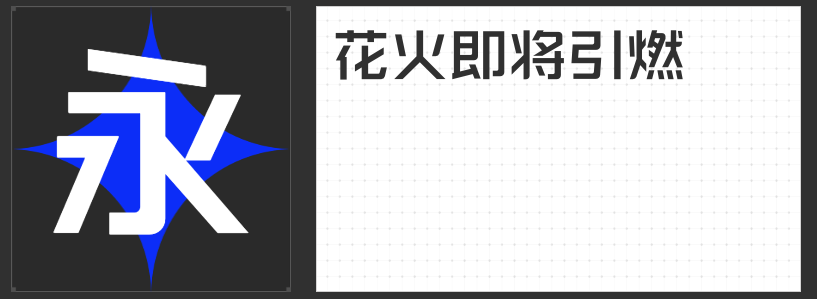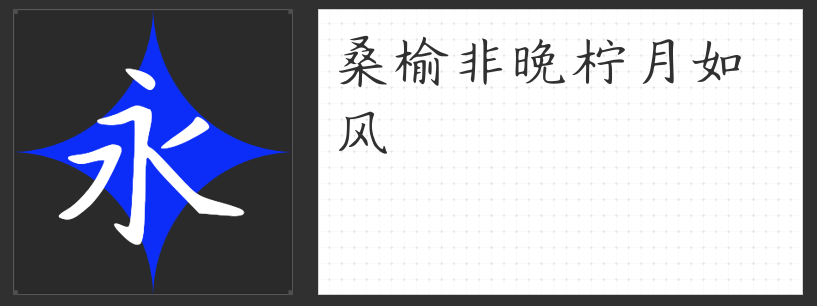
时光回溯:四款怀旧感字体的美学密码
在当代设计追求极简与科技感的浪潮中,怀旧风格以其独特的情感张力与文化厚度,成为连接过去与现在的视觉桥梁。以下四款字体以各自的方式诠释了时光的沉淀感,为怀旧主题设计注入灵魂。
一、励字勇敢黑简 中黑
这款无衬线字体以粗壮笔划构建视觉骨架,横竖均匀的线条如同机械零件般精准,撇捺收笔处的钝角处理消解了锐利感,赋予文字沉稳的工业气质。其设计语言暗合20世纪中叶的印刷美学,在标志设计与标题排版中,能瞬间唤起人们对老式招牌、工厂标语的记忆联想。笔划间的留白处理克制而节制,既保证了阅读清晰度,又通过负空间营造出年代特有的疏离感。
二、云书法三行魏碑体
取法北魏墓志的这款楷书字体,在工整结构中注入书法灵韵。笔划起收处的方峻与行笔间的婉转形成微妙张力,既保留了碑刻的古朴厚重,又通过流畅的曲线赋予文字呼吸感。其横细竖粗的对比关系,暗合传统活字印刷的视觉逻辑,在正文排版中能营造出古籍般的阅读韵律。当用于标题设计时,略带残缺的笔划边缘更添岁月侵蚀的质感。
三、造字侠永刚漆书简繁
模拟漆器书写的毛笔字体,以浓重墨色与飞白效果构建视觉层次。笔划起承转合间保留的手写痕迹,如同匠人挥毫时留下的时间印记。其框架结构借鉴了传统楹联书法的布局智慧,在端庄中暗藏动态平衡。繁简双版本的设计考量,既满足现代设计的国际化需求,又保留了汉字演化的历史纵深感,特别适合需要传递文化厚度的包装与印刷设计。
四、励字舒体简繁
这款融合五体书风的创意字体,以飘逸的曲线重构汉字结构。弯钩处如盘马之姿,捺画舒展似长袖舞动,在恣肆挥洒中保持着法度严谨。其设计灵感源自明清文人尺牍,通过现代数字化技术重新解构传统书法,既保留了手写体的温度,又提升了多场景适用性。当用于品牌视觉系统时,能构建出兼具古典雅韵与当代审美的独特气质。
这四款字体如同四把时光钥匙,分别开启工业记忆、碑刻文明、匠人精神与文人雅趣的视觉宝库。设计师可根据具体需求,选择与怀旧主题最契合的字体语言,让设计作品在时光长河中泛起独特的涟漪。